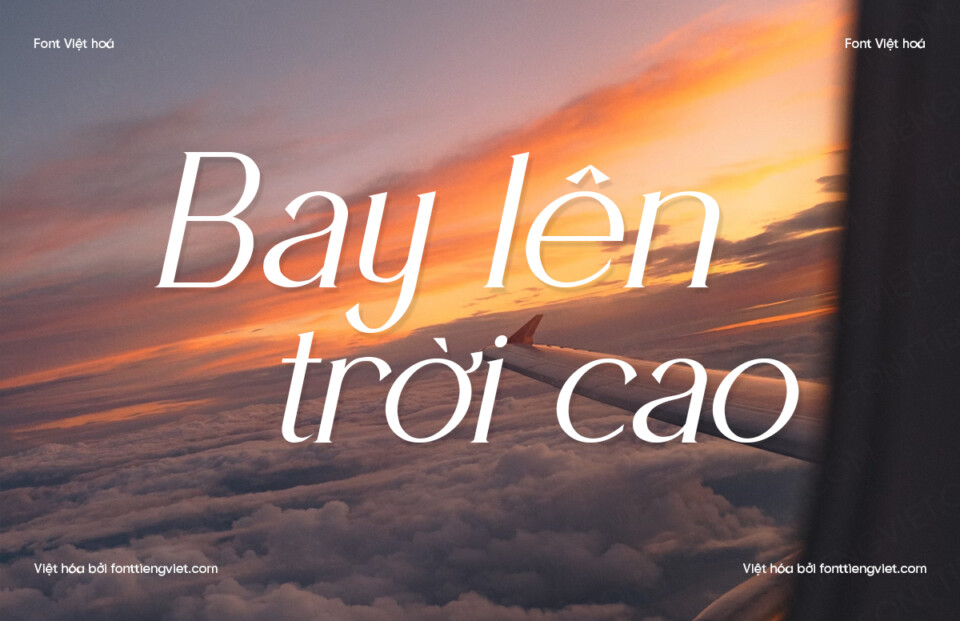
Font Việt hóa 1FTV VIP Vocago Italic
Font Việt hóa 1FTV VIP Vocago Italic – Đỉnh Cao Sáng Tạo Cho Thiết Kế Hiện Đại
Trong thế giới thiết kế đồ họa ngày nay, việc lựa chọn một bộ font chữ phù hợp đóng vai trò quyết định đến sự thành công của một sản phẩm truyền thông. Đặc biệt đối với các nhà sáng tạo nội dung tại Việt Nam, nhu cầu tìm kiếm các bộ font đã qua xử lý dấu tiếng Việt luôn ở mức cao. Một trong những cái tên đang thu hút sự chú ý mạnh mẽ chính là Font Việt hóa 1FTV VIP Vocago Italic. Đây không chỉ là một công cụ trình bày văn bản thông thường mà còn là sự kết hợp tinh tế giữa nét đẹp cổ điển và hơi thở hiện đại. Việc sử dụng Font Miễn Phí chất lượng như Vocago Italic giúp các bạn học sinh, sinh viên và giáo viên dễ dàng tạo ra những bài thuyết trình ấn tượng hoặc các ấn phẩm học đường bắt mắt mà không gặp lỗi hiển thị ký tự. Với đường nét nghiêng thanh thoát, bộ font này mang lại cảm giác chuyển động linh hoạt và đầy chuyên nghiệp.
Đặc điểm nổi bật của Font Việt hóa 1FTV VIP Vocago Italic
Phong cách thiết kế sang trọng và tinh tế
Font Việt hóa 1FTV VIP Vocago Italic nổi bật với cấu trúc các con chữ được tạo hình vô cùng tỉ mỉ. Khác với những phông chữ nghiêng thông thường dễ gây cảm giác rối mắt, Vocago Italic giữ được sự cân bằng hoàn hảo giữa độ nghiêng và khoảng cách giữa các chữ cái. Điều này giúp văn bản luôn đảm bảo tính dễ đọc ngay cả khi được trình bày ở kích thước nhỏ. Các nét thanh và nét đậm được phân bổ một cách nhịp nhàng, tạo nên một tổng thể thị giác hài hòa, phù hợp cho nhiều mục tiêu thiết kế khác nhau từ làm tiêu đề báo cáo đến trang trí bìa sách học thuật.
Khả năng tương thích và tối ưu hóa tiếng Việt
Điểm mạnh lớn nhất của Font Việt hóa 1FTV VIP Vocago Italic chính là bộ dấu tiếng Việt được thiết kế chuẩn chỉnh. Đội ngũ kỹ thuật của 1FTV đã dành nhiều tâm huyết để tinh chỉnh các dấu thanh như huyền, sắc, hỏi, ngã, nặng sao cho không bị đè lên chữ cái hoặc gây mất cân đối. Nhờ vậy, người dùng có thể hoàn toàn yên tâm khi soạn thảo văn bản tiếng Việt mà không lo hiện tượng “lỗi font” thường thấy ở các bộ font ngoại nhập chưa qua việt hóa. Sự mượt mà trong từng nét chữ giúp tôn vinh vẻ đẹp của ngôn ngữ dân tộc trong các tác phẩm nghệ thuật số.
Ứng dụng Font Việt hóa 1FTV VIP Vocago Italic trong học tập và công việc
Thiết kế bài giảng và tài liệu học tập
Đối với giáo viên và các bạn học sinh, Font Việt hóa 1FTV VIP Vocago Italic là một trợ thủ đắc lực trong việc làm mới các slide bài giảng. Thay vì sử dụng những phông chữ mặc định nhàm chán, việc áp dụng Vocago Italic vào các đề mục quan trọng sẽ giúp bài học trở nên sinh động và thu hút sự chú ý của học sinh hơn. Tính chất nghiêng nhẹ nhàng của font chữ này cực kỳ phù hợp để làm nổi bật các câu trích dẫn, ghi chú quan trọng hoặc các thuật ngữ chuyên môn cần nhấn mạnh trong tài liệu ôn tập.
Sáng tạo ấn phẩm truyền thông học đường
Trong các hoạt động ngoại khóa hay sự kiện nhà trường, nhu cầu thiết kế poster và băng rôn là rất lớn. Font Việt hóa 1FTV VIP Vocago Italic với vẻ ngoài hiện đại và năng động là lựa chọn ưu tiên để tạo nên sự khác biệt. Bạn có thể kết hợp nó với các font chữ không chân khác để tạo nên sự tương phản thú vị. Dù là thiết kế thiệp mời lễ tốt nghiệp hay làm banner cho câu lạc bộ, bộ font này vẫn luôn giữ được sự chỉn chu và đẳng cấp, giúp nâng tầm hình ảnh của tập thể lớp và nhà trường.
Kết luận về bộ Font Việt hóa 1FTV VIP Vocago Italic
Tổng kết lại, Font Việt hóa 1FTV VIP Vocago Italic là một lựa chọn tuyệt vời dành cho bất kỳ ai đang tìm kiếm sự phá cách nhưng vẫn giữ được nét thanh lịch trong thiết kế. Với bộ mã Unicode đầy đủ và dấu tiếng Việt sắc nét, sản phẩm này xứng đáng có mặt trong bộ sưu tập tài nguyên đồ họa của bạn. Việc tiếp cận các nguồn Font Miễn Phí, Font Việt Hóa, Font Việt hóa 1FTV VIP Vocago Italic sẽ giúp cộng đồng thiết kế Việt Nam ngày càng phát triển mạnh mẽ hơn. Hãy thử nghiệm ngay bộ font này để cảm nhận sự khác biệt trong từng khung hình và biến những ý tưởng sáng tạo của bạn thành hiện thực một cách chuyên nghiệp nhất.